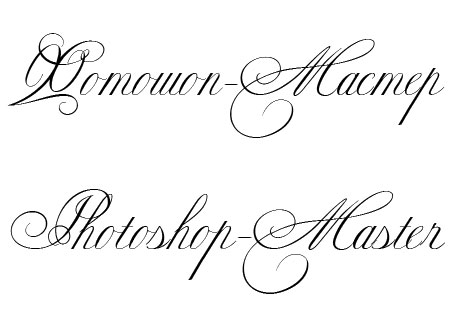
Большое спасибо! Использовал два раза, оба шрифт смотрелся великолепно! Даже не поверили, что я делал (не зря старался :))
русский язык не поддерживает
О, класс! Теперь открытки можно делать к НГ как раз! Спс!
о_О, я так люблю такие елегантные шрифти, спасибо!!! =) ^_^